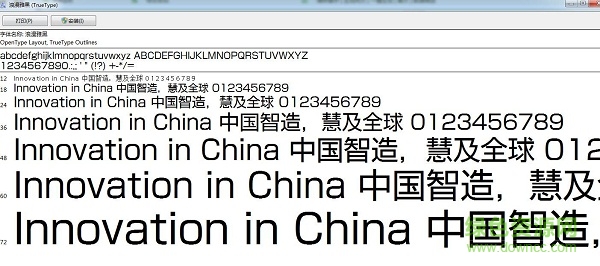
浪漫雅黑ttf
浪漫雅黑字體是一款有著超高清晰度的精品無襯線字體,字形飽滿,結(jié)構(gòu)舒展,線條簡潔十分易于閱讀,浪漫雅圓和微軟雅黑字體本站都有提供,需要的朋友快來免費(fèi)下載吧!
浪漫雅黑字體
黑體字體介紹
“黑體”是一類字體的總稱,有很多字體都屬于這個(gè)范疇,黑體”在日文中稱為ゴシック體,直譯即哥特體;但在歐洲國家里,哥德體指的是Blackletter(日文也根據(jù)「Blackletter」的音,稱作「ブラックレター」)!